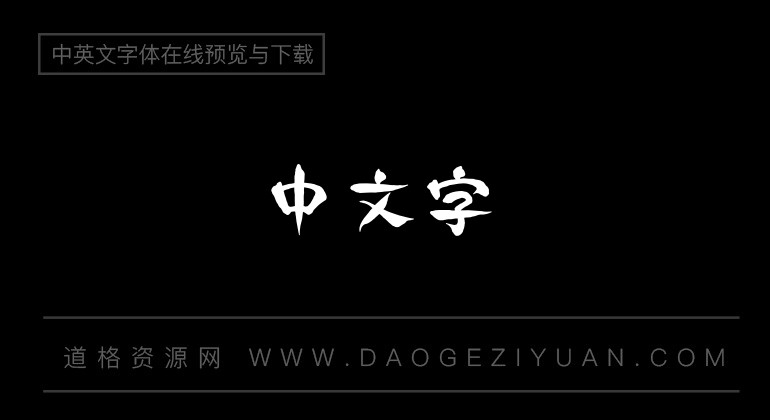
蒙纳简岚山隶书
? 蒙纳简岚山隶书是一种中国传统的书法字体,它源自宋代蒙古文书法,传入中国,经历了宋、元、明、清等历史时期,经过不断的发展,形成了一种独特的书法字体。蒙纳简岚山隶书的特点是字体比较粗犷,笔画粗细变化较大,线条流畅,有着浓厚的蒙古风格。它比较适合书写蒙古文,也可以用来书写汉字,但是汉字的书写效果比较差,不太适合汉字书写。
蒙纳简岚山隶书是一款非常不错的手写艺术字体,具有很好的视觉感,适合于文化类的宣传设计、商业类品牌的广告和产品包装设计以及个性化文字排版等较多场景。